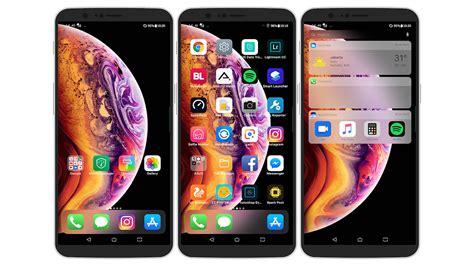
Ubah Tampilan Font Android Anda Jadi Seperti IPhone
Ubah Tampilan Font Android Anda Jadi Seperti iPhone
Guys, pernah nggak sih kalian ngeliat tampilan font di iPhone dan mikir, “Wah, keren banget nih! Pengen deh di HP Android gue juga kayak gitu.” Tenang aja, kalian nggak sendirian! Banyak banget dari kita yang suka sama font khas iPhone yang simpel, elegan, dan kelihatan premium . Nah, di artikel ini, gue bakal ngasih tau cara gampang buat bikin tulisan di HP Android kamu jadi mirip banget sama yang ada di iPhone. Nggak perlu jadi hacker kok, cuma modal HP Android dan sedikit sentuhan kreatif aja, dijamin tampilan HP kamu bakal langsung naik level! Siap-siap deh buat bikin temen-temen kamu pada iri!
Kenapa Sih Font iPhone Itu Keren Banget?
Sebelum kita mulai ke tutorialnya, ada baiknya kita ngerti dulu kenapa sih font iPhone itu banyak banget penggemarnya. Menurut gue pribadi, ada beberapa alasan utamanya. Pertama , font iPhone itu punya kesan yang clean dan minimalis. Nggak ada embel-embel yang aneh-aneh, bentuknya jelas, dan gampang dibaca. Ini penting banget lho, apalagi buat kita yang sering banget ngeliat layar HP seharian. Tampilan yang clean ini bikin mata nggak gampang lelah, guys. Kedua , font bawaan iPhone, yang biasanya dikenal dengan nama San Francisco (SF) Pro atau varian lainnya seperti Helvetica Neue (pada iOS versi lama), punya design yang sangat balanced . Artinya, proporsi antara huruf besar, huruf kecil, angka, dan simbol itu pas banget. Jarak antar hurufnya juga diatur sedemikian rupa biar enak dilihat. Keseimbangan ini yang bikin font iPhone kelihatan profesional dan mahal. Ketiga , ada unsur brand identity yang kuat. Apple itu jago banget soal branding , dan salah satu elemennya adalah konsistensi desain, termasuk pemilihan font . Setiap kali kita lihat font itu, langsung keinget sama produk-produk Apple yang sleek dan canggih. Jadi, bukan cuma soal tampilannya aja, tapi juga soal experience yang ditawarkan. Nah, dengan keinginan untuk mendapatkan estetika yang sama di HP Android kita, muncul berbagai cara kreatif untuk mengadopsi gaya font iPhone. Ini menunjukkan bahwa tampilan visual memang punya peran besar dalam kepuasan pengguna smartphone, dan kita sebagai pengguna bebas untuk mempersonalisasi perangkat kita sesuai selera. Terlebih lagi, di era digital ini, personalisasi bukan lagi sekadar keinginan, melainkan sebuah kebutuhan untuk mengekspresikan diri. Mengubah font adalah salah satu cara termudah namun paling efektif untuk memberikan sentuhan personal pada HP Android kamu, membuatnya terasa lebih unik dan mencerminkan gaya kamu sendiri, seolah-olah kamu sedang menggunakan perangkat premium dari Apple.
Metode 1: Menggunakan Aplikasi Pengubah Font (Cara Paling Gampang!)
Metode 2: Menggunakan Tema Kustom (Lebih Totalitas!)
Kalau kamu ngerasa pakai satu font aja kurang greget, gimana kalau kita ubah sekalian tema HP kamu biar nuansanya makin dapet? Nah, ini dia nih cara yang lebih totalitas, yaitu dengan menggunakan tema kustom atau launcher yang punya tampilan mirip iOS. Aplikasi launcher kayak Launcher iOS 15/16/17 (nama ini sering ganti-ganti tergantung versi iOS terbaru) di Play Store bisa ngubah tampilan home screen , app drawer , ikon aplikasi, sampai bahkan notifikasi kamu jadi mirip banget sama iPhone. Gila kan? Kamu tinggal download dan install launcher ini, terus atur sebagai default launcher . Setelah itu, kamu bakal disuguhin tampilan home screen yang ikonnya tersusun rapi kayak di iPhone, lengkap dengan widget ala iOS. Nggak cuma itu, banyak launcher iOS ini juga udah bundling sama paket ikon yang desainnya mirip ikon aplikasi bawaan iPhone. Jadi, aplikasi-aplikasi kamu kayak WhatsApp, Instagram, atau YouTube bakal punya ikon baru yang estetik banget. Nah, soal font , biasanya launcher ini juga udah ngikutin font default iOS, atau kamu bisa atur lagi font di dalam pengaturan launcher -nya. Jadi, ini paket lengkap banget, guys! Dari home screen , ikon, sampai font , semuanya bisa kamu ubah biar serasa pakai iPhone. Tips buat kamu yang mau coba ini: pilih launcher yang ratingnya bagus dan banyak di- download , biar nggak salah pilih aplikasi yang buggy atau penuh iklan. Baca juga review dari pengguna lain. Perhatikan juga spesifikasi HP kamu, karena launcher yang kompleks kadang butuh spek HP yang lumayan biar nggak ngelag. Kelebihan pakai launcher kayak gini adalah kamu bisa dapetin pengalaman pakai iPhone secara visual tanpa harus beli HP-nya. Tapi, ingat ya, ini cuma perubahan tampilan luar aja. Fungsi dan performa HP kamu tetap seperti HP Android pada dasarnya. Kelemahannya, kadang beberapa fitur khas Android yang kamu suka bisa jadi agak tersembunyi atau berubah cara aksesnya karena udah disesuaikan sama gaya iOS. Tapi, kalau tujuannya emang buat gaya, ini solusi yang paling mantap! Plus, kamu juga bisa coba download paket tema atau ikon yang spesifik bertema iOS dari toko tema bawaan HP kamu (kalau ada), ini biasanya lebih ringan daripada pakai launcher pihak ketiga. Pokoknya, opsi tema kustom ini cocok buat kamu yang suka banget sama keseluruhan tampilan dan nuansa iOS.
Metode 3: Menggunakan Kustomisasi Lanjutan (Buat yang Hobi Ngoprek!)
Tips Tambahan Biar Makin Mirip iPhone Banget!
Selain mengganti font , ada beberapa trik kecil lagi nih biar tampilan HP Android kamu makin totalitas mirip iPhone. Pertama, atur tata letak ikon di home screen . iPhone itu ikonnya rapi, berjarak, dan biasanya nggak ada widget yang terlalu ramai di home screen utama. Coba tata ikon aplikasi yang sering kamu pakai di baris-baris rapi. Kedua, gunakan wallpaper khas iOS . Cari aja di Google dengan kata kunci “iPhone wallpaper” atau “iOS wallpaper”. Pilih gambar yang simpel, estetik, dan punya warna yang kalem. Ketiga, ganti paket ikon aplikasi . Seperti yang udah gue sebut di metode tema, banyak launcher atau aplikasi ikon pack di Play Store yang bisa ngubah tampilan ikon aplikasi kamu jadi mirip ikon bawaan iPhone. Cari yang namanya mirip-mirip “iOS icon pack” atau “iPhone UI icon”. Keempat, perhatikan font di notifikasi dan status bar . Kalau kamu pakai launcher yang udah mirip iOS, biasanya ini udah otomatis ikut berubah. Tapi kalau belum, coba cari pengaturan di launcher atau aplikasi tema kamu. Kelima, gunakan keyboard ala iPhone . Ada aplikasi keyboard di Play Store yang bisa kamu setting biar tampilannya mirip keyboard iPhone, lengkap dengan font dan layout -nya. Terakhir, atur animasi layar . Kalau HP kamu support, coba kecilin atau ubah durasi animasi transisi biar terasa lebih responsif kayak iPhone. Kombinasikan semua tips ini, dan dijamin deh HP Android kamu bakal kelihatan kayak kembaran iPhone dari jauh. Ingat, personalisasi itu kunci, jadi jangan ragu buat bereksperimen sampai nemu tampilan yang paling bikin kamu happy dan nyaman dipakai sehari-hari. Selamat mencoba, guys!